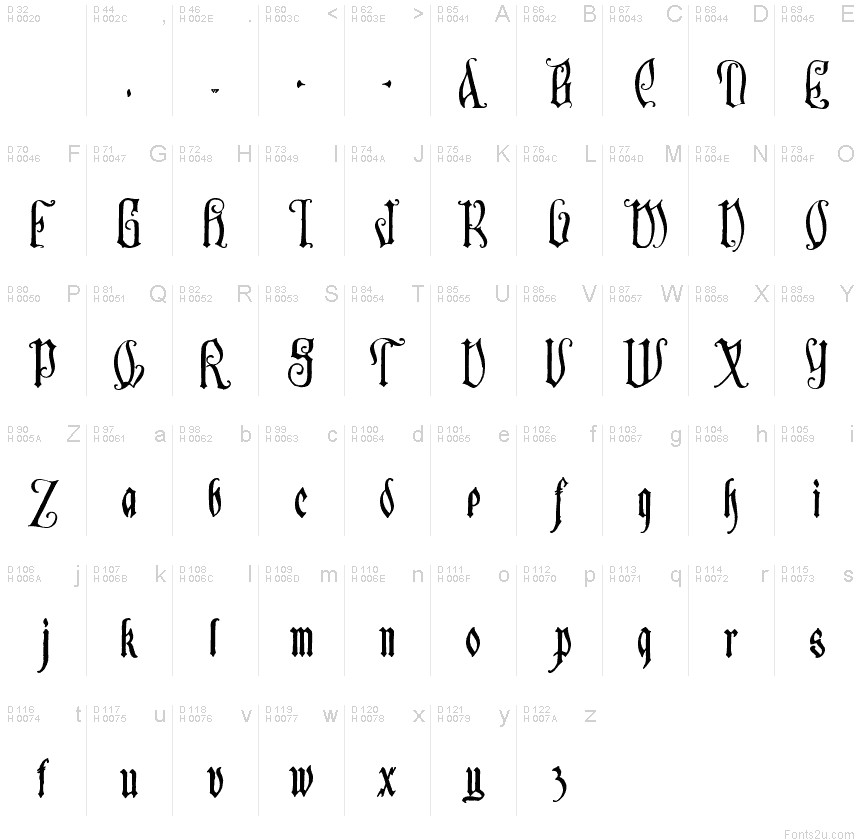
Sauerkraut od TypeType to darmowy, średniowieczny krój blackletter, oddający gęsty, rzemieślniczy klimat dawnych niemieckich szyldów i tytułów książkowych. Litery opierają się na ostrych pionowych cięciach i zawijasach, zwłaszcza w formach otwierających, dzięki czemu cały krój sprawia wrażenie uroczystego, choć raczej teatralnego niż surowo kościelnego.
Świetnie sprawdzi się na etykietach piw, w identyfikacji wizualnej tawern, na plakatach festiwalowych, okładkach albumów i w tytułach, gdzie ten historyczny ciężar pozwala szybko zbudować klimat. Jako darmowy font, idealnie nadaje się również do krótkich nagłówków, monogramów i inicjałów – jego zahaczone krzywizny oraz wąskie, łamane kreski niosą ze sobą charakter nawet przy minimalnej ilości tekstu.